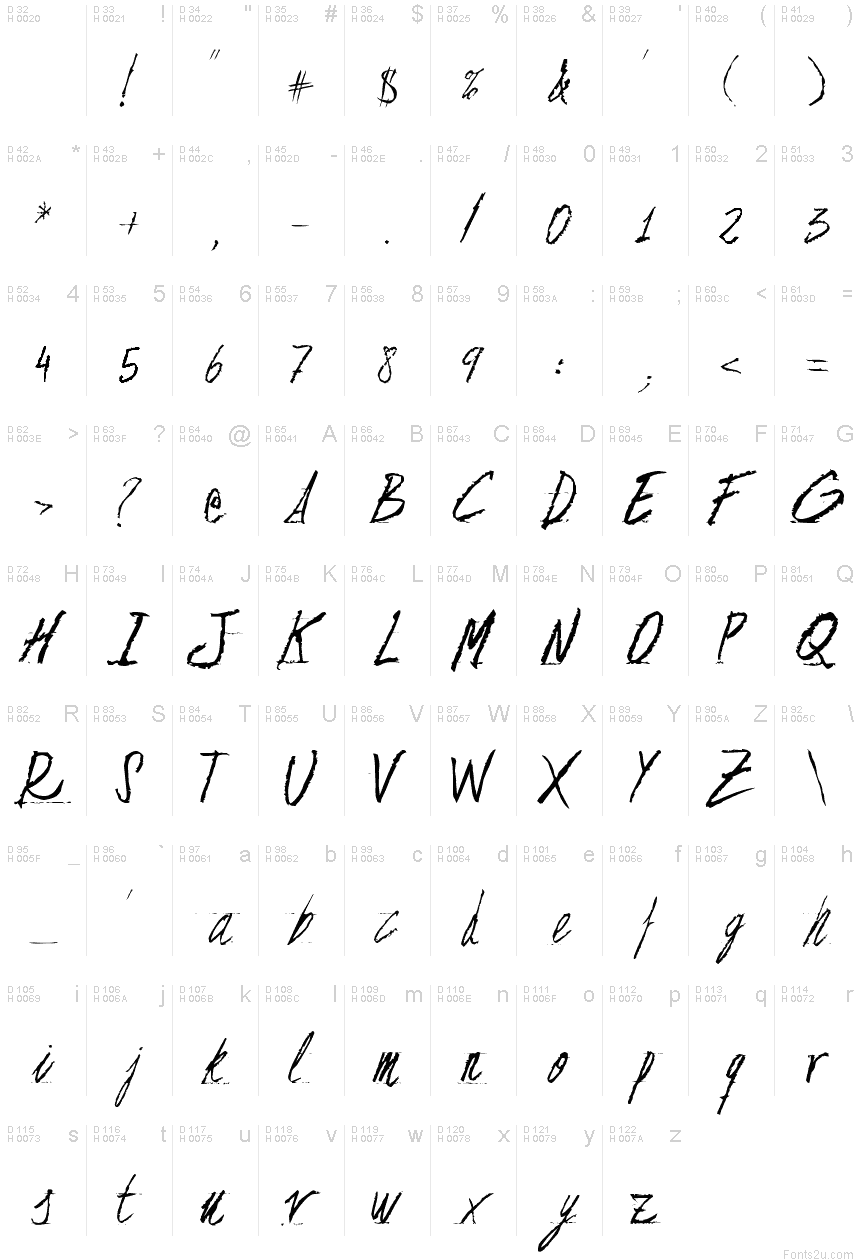
Floja Script من Lagalga هو خط مجاني بأسلوب الفرشاة يبدو وكأنه رُسم على الورق بفرشاة شبه جافة. تمنح حروفه الطويلة والمائلة وحوافه غير المنتظمة وملمسه المخطط كل كلمة طاقة عفوية نابضة بالحياة، كما لو كانت قد كُتبت في لحظة تدفق عاطفي. تبدو المسافات بين الحروف حرة وتلقائية، مما يجعل الأسطر تتنفس وتتداخل بطريقة تمنح التصميم مظهراً خاماً وغير متكلف.
باستخدام Floja Script، يمكنك إضافة لمسة جريئة إلى الملصقات، وأغلفة الألبومات، وتصاميم وسائل التواصل الاجتماعي، والعبوات المبتكرة، وأغلفة الكتب، ومنشورات الفعاليات، أو طباعة الملابس المميزة. يتألق هذا الخط المجاني عند استخدامه بأحجام كبيرة، حيث تبرز ضربات الفرشاة الخشنة وتناثر الحبر بشكل واضح، لذا لا تتردد في تكبير حجمه. وللحصول على تباين أنيق، ادمج Floja Script مع خط بلا زوائد (sans-serif) هندسي بسيط في النصوص الفرعية الأصغر.